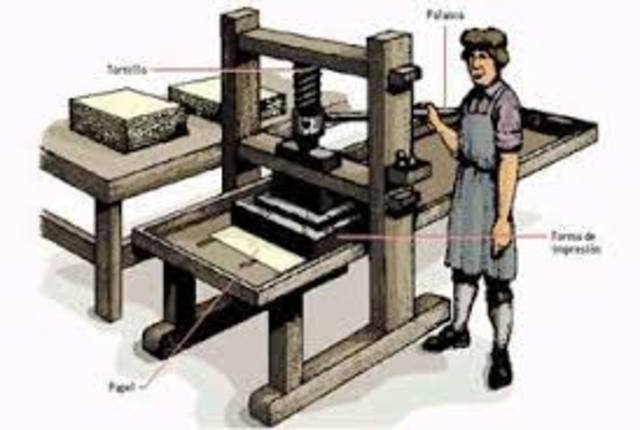
Historia de la Tipografía
• PRIMERA IMPRENTA DE ITALIA Conrad Sweynhym y Arnold Pannartz trabaja en la primera imprenta de Italia en el Monasterio de Benedicto de Subiaco, caligrafía humanistica.
PRIMERA IMPRENTA DE ITALIA Conrad Sweynhym y Arnold Pannartz trabaja en la primera imprenta de Italia en el Monasterio de Benedicto de Subiaco, caligrafía humanistica.
SE IMPRIME EL PRIMER LIBRO Se imprimió el primer libro en inglés bajo el título de Recuyell of the Historyes of troye del Autor: Raold le Fèvre
INTRODUCCIÓN DE LA IMPRENTA A FRANCIA Gullaume Le Roy introdujo la imprenta a Lyon Francia
SE FUNDA LA IMPRENTA EN VENECIA ESPAÑA Almus manutis fundó su imprenta Aldina en Venecia España
SE CREA EL PRIMER MANUAL DE ESCRITURA Ludovico Vicentino degli Arriaghi creó el primer manual de escritura e imprime el segundo
SIGLO DE ORO DE LA TIPOGRAFÍA FRANCESA DENTRO DE LOS PERSONAJES IMPORTANTES SE DESTACAN GEOFFROY TORY CLAUDE GARAMOND, TORY FUE EL REFORMADOR DE LA LENGUA FRANCESA E INCLUYÓ EL APOSTROFE, EL ACENTO, CEDILLA LA OBRA MÁS IMPORTANTE FUE: CHAMPFLEURY
PRIMER FUNDIDOR DE TIPOS DE TRABAJO CLAUDE GARAMOND FUE EL PRIMER FUNDIDOR DE TIPOS DE TRABAJO
IMPERSOR PERSONA DEL PAPA Antonio Vlado se convierte en el impresor papal
EL REY MANDA A APLATIN A TRABAJAR EL REY FELIPE II DE ESPAÑA COMISIONÓ A CHRISTOPHE PLATÍN PARA TRABAJAR EN LA BIBLIA REGIA IMPRESA EN 5 IDIOMAS, SU APORTE FUE EL USO DE GRABADOS EN LÁMINA DE COBRE PARA ILUSTRAR LOS LIBROS
GRAN PROCESO DE IMPRESIÓN, EN ESTE PERIODO SE IMPRIMIÓ FRECUENTEMENTE LA BIBLIA DEL REY JAMES Y EN ESPAÑA SE IMPRIMIÓ EL QUIJOTE DE LA MANCHA DE MIGUEL DE CERVANTES
PRIMER PERIODICO EUROPEO APARECE EL PRIMER PERIODICO EUROPEO BAJO EL NOMBRE DE AVISA RELATIÓN ODER ZEITUG SE PUBLICA EN AMBURGO Y ESTRASBURGO
SE IMPRIMEN LIBROS DE BOLSILLO SE IMPRIME LOS PRIMEROS LIBROS DE BOLSILLO QUE HICIEERON FAMOSO A LOUIS ELVERIR
LLEGA LA IMPRENTA A OXFORD SE ESTABLECE LA IMPRENTA EN LA UNIVERSIDAD DE OXFORD
INICIA LA DINASTÍA DIDOT DE FRANCOIS INICIA EN LA CIUDAD DE PARÍS LA DINASTÍA DIDOTY SE ESTABLECE LA IMPRENTA Y LIBRERÍA
PRIMERA TABLA DE PROPORCIONES
Sistema Fournier
Los antecedentes de dicho sistema tipográfico se deben a Pierre Simón Fournier (1712-1768), quién publicó en 1737 un sistema o Tabla de Proporciones para la fundición sistemática de caracteres que llamó duodecimal.
LIBRO DE MODELOS
PIERRE SIMÓN ABRE SU PROPIA FUNDICIÓN Y PUBLICA EL LIBRO DE MODELOS, ESTE TRAE 4600 CARACTERES DISEÑADOS Y TALLADOS EN 6 AÑOS
SE CREA EL SISTEMA DE PUNTOS
FRANCOIS AMBROISE CREA EL SISTEMA DE PUNTOS QUE SE USA EN FRANCIA
REDISEÑO DE LAS LETRA ROMANAS
SE REDISEÑÓ ÑAS FORMAS DE LAS LETRAS ROMANAS CON UN ASPECTO MÁS MATEMÁTICO, GEOMETRICO Y MECÁNICO
LORD STANHOPE
DESARROLLÓ MAQUINA IMPRESORA CONSTRUIDA DE HIERRO FUNDIDO
ROBERT THORNE ROBERT THORNE
ALUMNO DE COTTELL EXHIBIÓ POR PRIMERA VEZ LETRAS GRIEGAS
1804 Friedrich Koenig
prepara una maquina para imprimir, operada a vapor, además obtiene la patente este invento, al imprimir hojas por hora
LA UNITED STATES
LA UNITED STATES FUNDADOR ASOCIACION ESTABLECIÓ UN COMITE PARA ESTUDIAR Y FOMULAR UN SISTEMA DE PUNTOS PARA LOS FINLANDESES AMERICANOS
1891 WILLIAN MORRIS FUNDÓ LA IMPRENTA KELMSCOTT
FILIPPO TOMMANSO MARINETT
IOS PINTORES AÑADEN FRAGMENTO DE PERIODICOS Y OTROS MATERIALES
PIET ZWART
CONTRIBUYE AL DESARROLLO DE LA TIPOGRAFIA MODERNA
INFLUENCIADO POR EL NEOPLASTISISMO
JAN TSCHICHOLD
fue el primero en racionalizar y formular sus nuevas ideas de forma sistemática y orientadas al trabajo diario del impresor
LA TECNICA FOTOCOMPOSICION
INICIA AL DESPLAZAR A LOS CARACTERES METALICOS